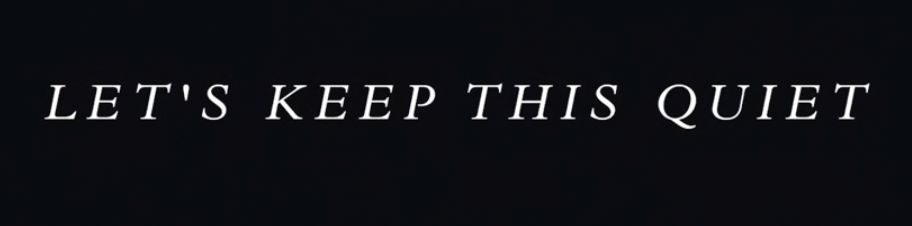
Suche Schriftart für Hochzeitseinladung
wir suchen für unsere Hochzeitseinladung die beigefügte Schriftart (mir und meiner Partnerin gefällt diese sehr).
Hallo @stefanodygi, es handelt sich um eine Garamond. Eine Garamond deshalb, weil es unzählige Varianten dieser Schrift gibt. Viele Versionen haben eigene kurisve Formen für die Versalien (Großbuchstaben), was sich unter anderem beim »Q« bemerkbar macht. Dein Beispiel hat diese eigene kursive Form nicht, das grenzt die Möglichkeiten ein wenig ein. Die Buchstaben der Kursiven sind zudem normalerweise schmaler als die der Aufrechten. Das scheint bei deinem Beispiel ebenfalls nicht der Fall zu sein. Möglicherweise ist das auch gar keine echte Kursive, sondern eine mechanisch verschrägte Aufrechte.
Wie dem auch sei; die URW-Garamond und die Stempel-Garamond gehen beispielsweise in die Richtung.
Edit: Hör auf @Kathrinvdm, ihre Diagnose passt besser.